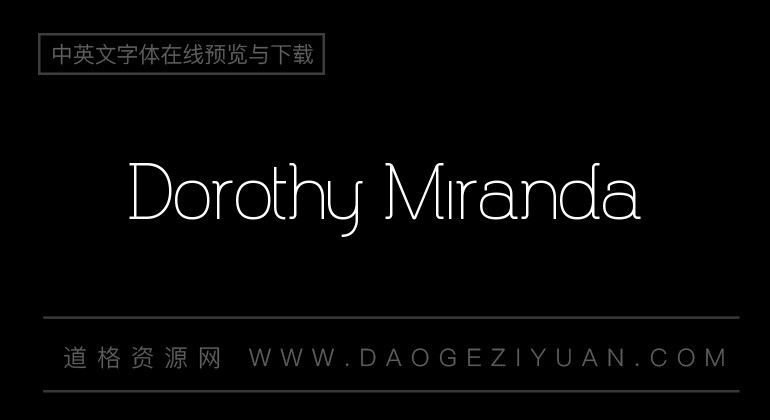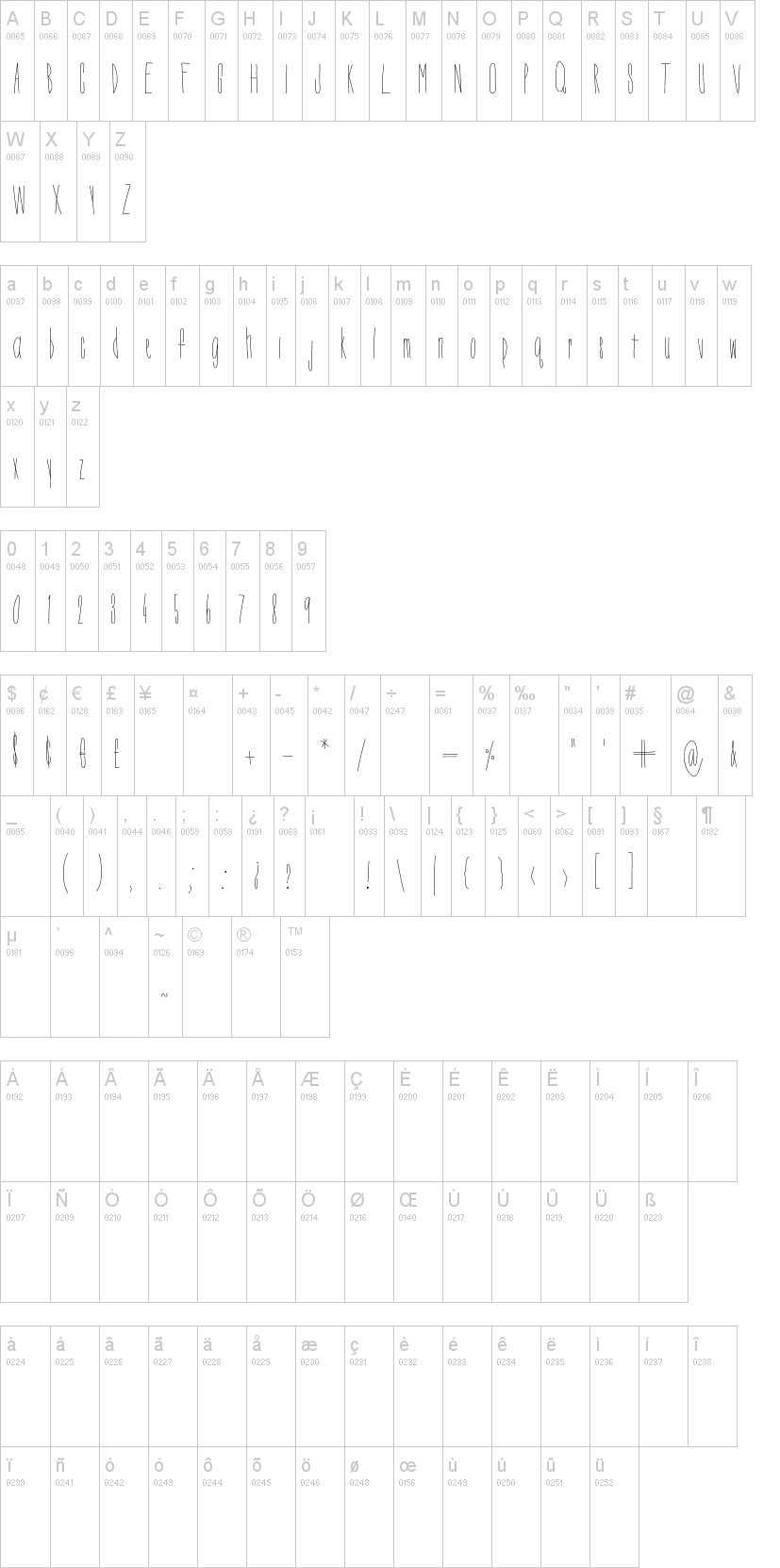
Dorothy Miranda
Dorothy Miranda 是一款美式手写体字体,由设计师 Miranda Roth 所设计。这款字体以细腻的笔画和温柔的曲线为特色,充满柔美的气息。它的特点是有一种温柔而清新的风格,十分适合用于绘制精致的文字。Dorothy Miranda 字体有一种灵动的特质,可以让文字看起来更加活泼有趣。它适合用于各种场景,包括礼品、卡片、图标等,能够为您的设计带来更多的活力和灵性。
Dorothy Miranda是一款非常不错的手写艺术字体,具有很好的视觉感,适合于文化类的宣传设计、商业类品牌的广告和产品包装设计以及个性化文字排版等较多场景。
Dorothy Miranda字符映射图